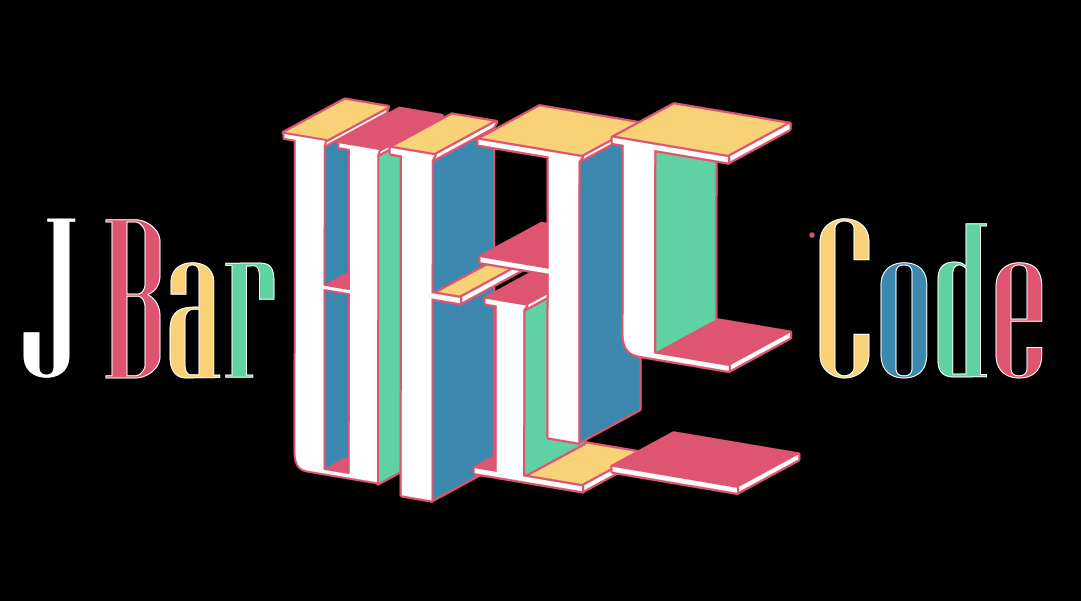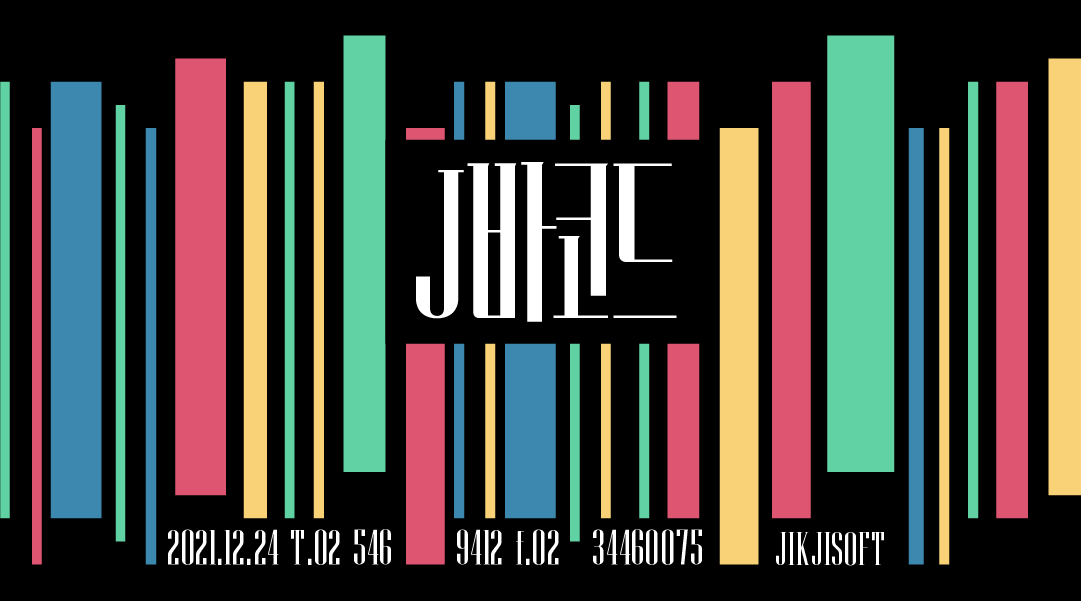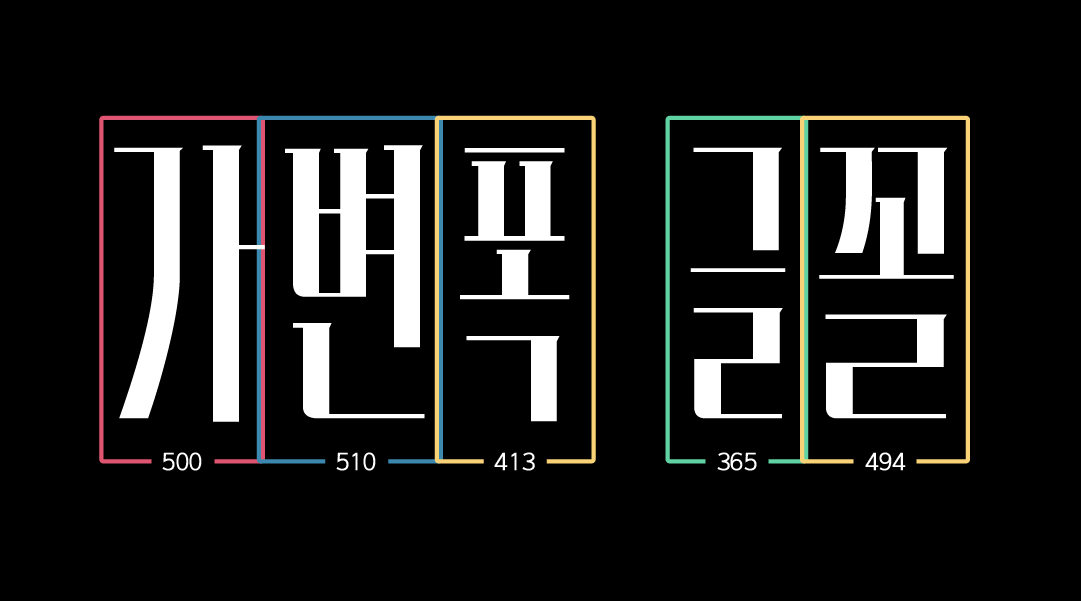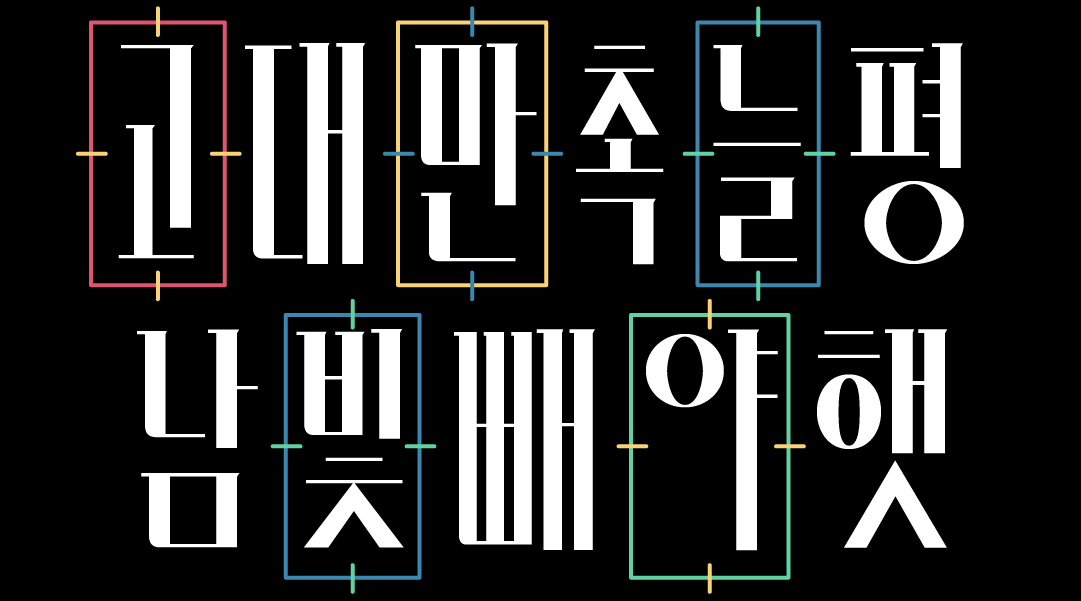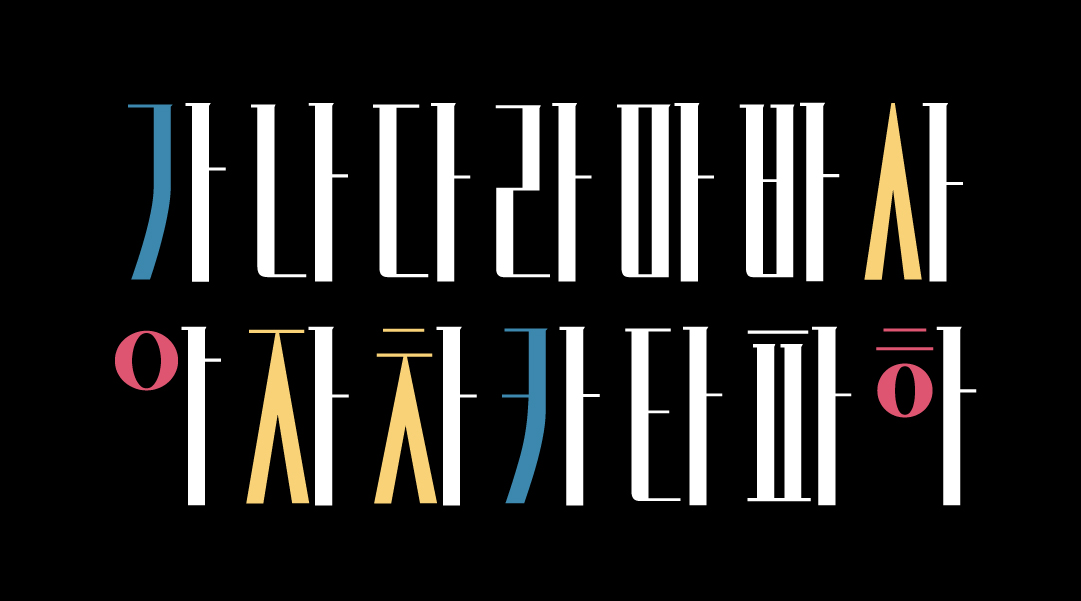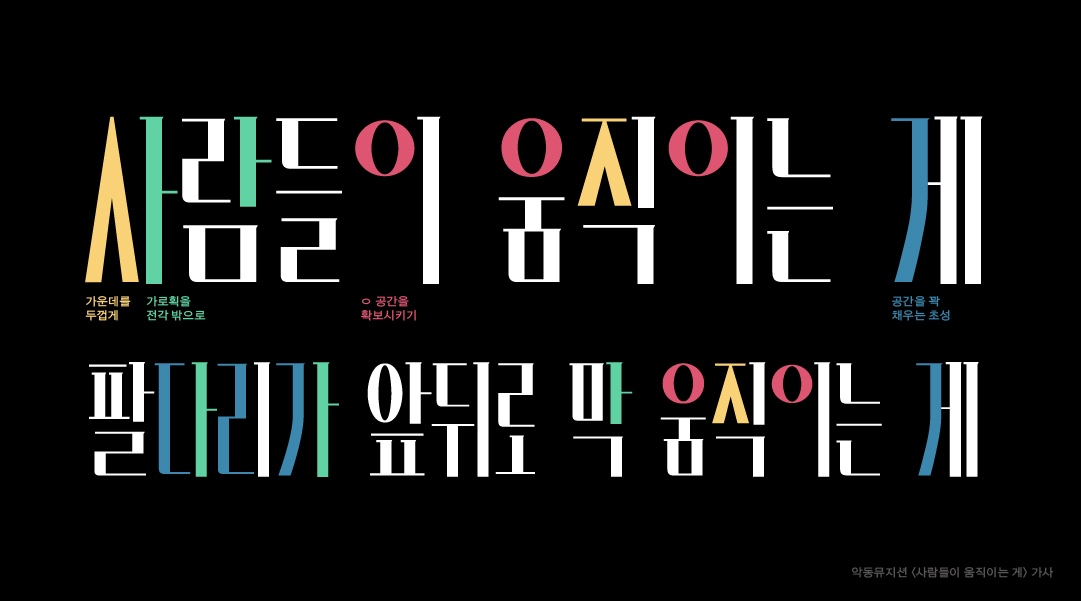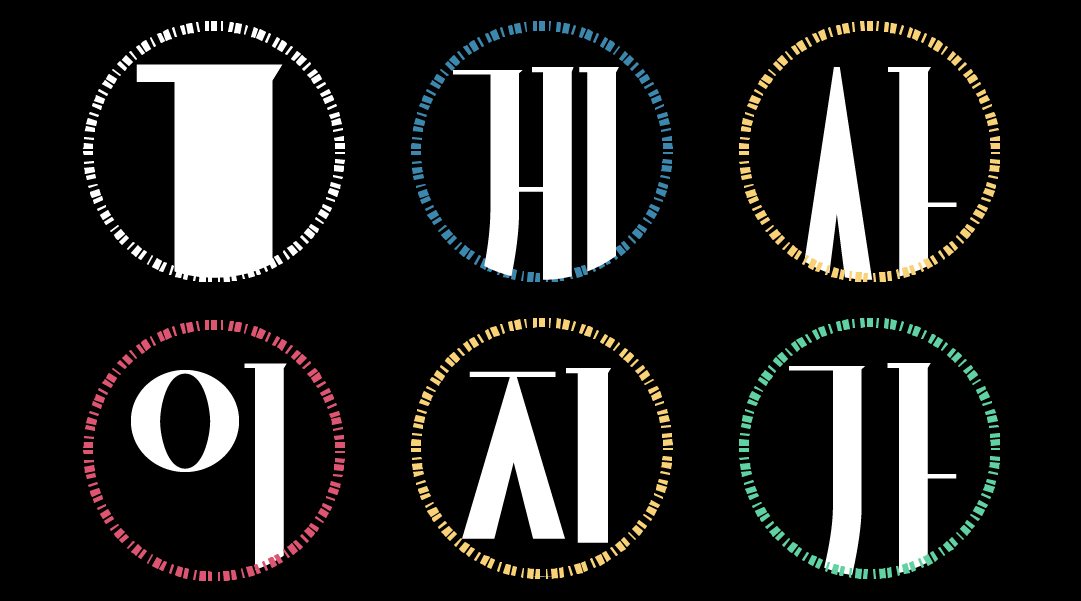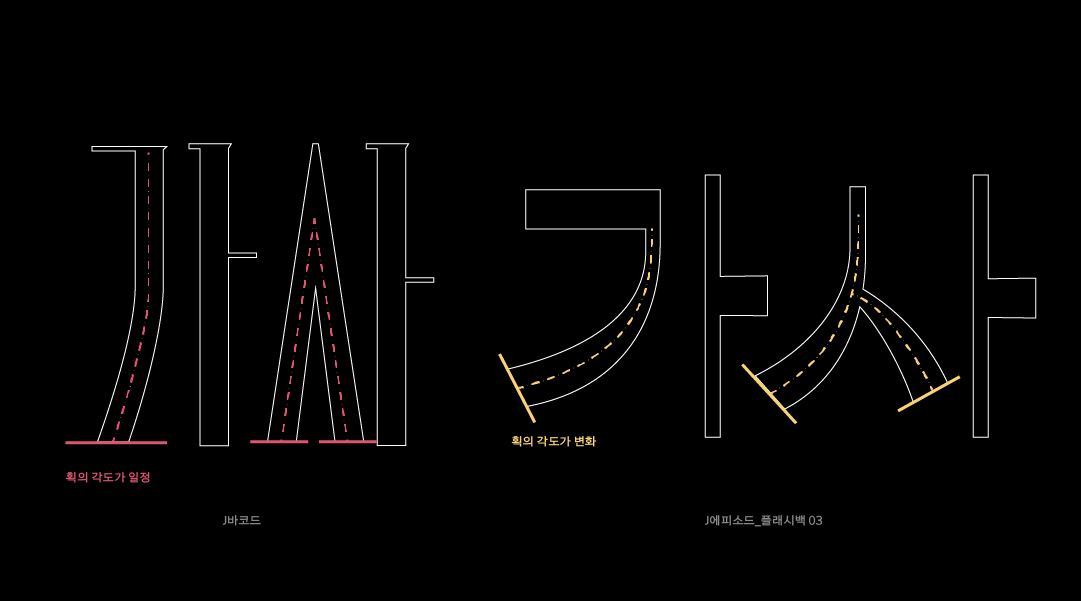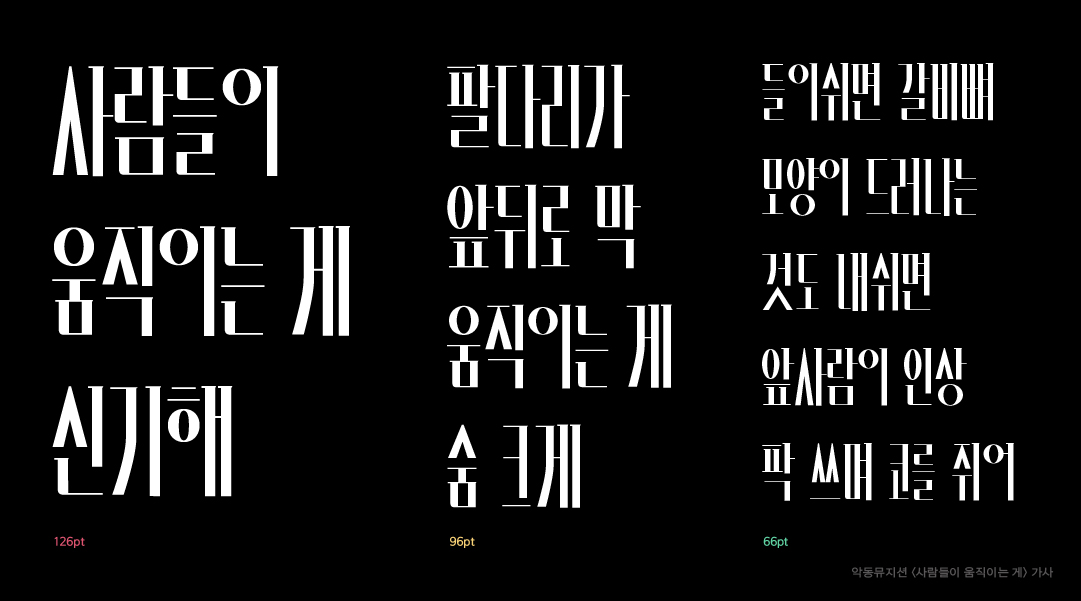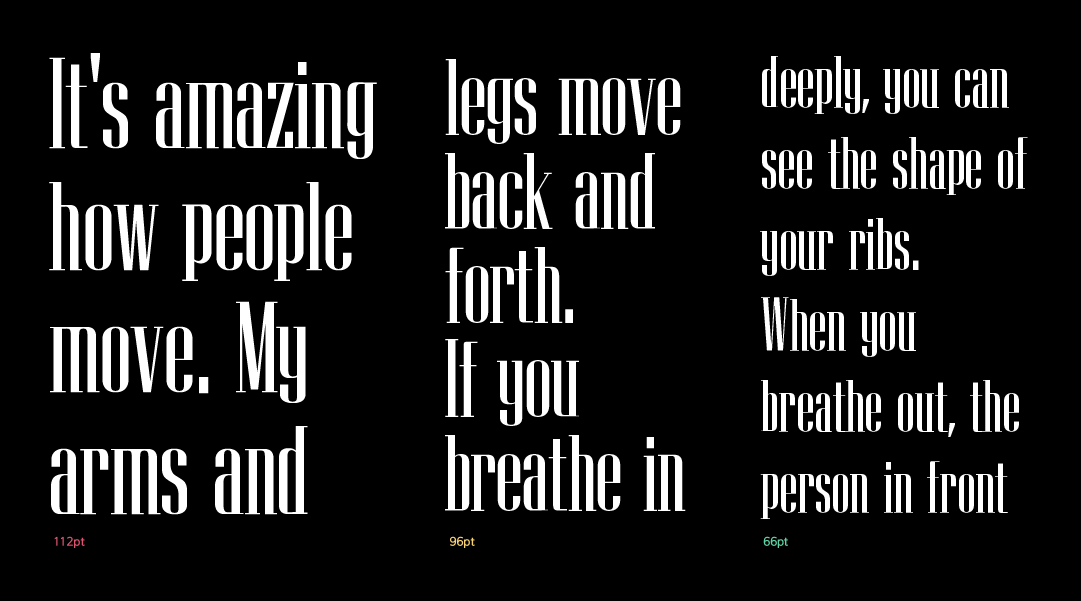
J바코드
J바코드는 직지소프트의 직지그래픽 폰트입니다. 출시일은 2021.01.01입니다. 1종으로 구성되어 있습니다.
다양한 컨셉으로 활용이 가능하고 독특한 디자인 요소가 많은 서체 시리즈. 개성있는 디테일로 시각적 재미를 더하고 풍부한 이야기를 담을 수 있는 서체이다.
장체로 설계된 네모 틀안에 꽉 찬 자소 디자인과 함께 극단적인 획 대비가 멀리서 보면 마치 바코드와 같이 생겼습니다. 개성 강한 헤드라인 서체로 활용할 수 있는 제목용 서체입니다.